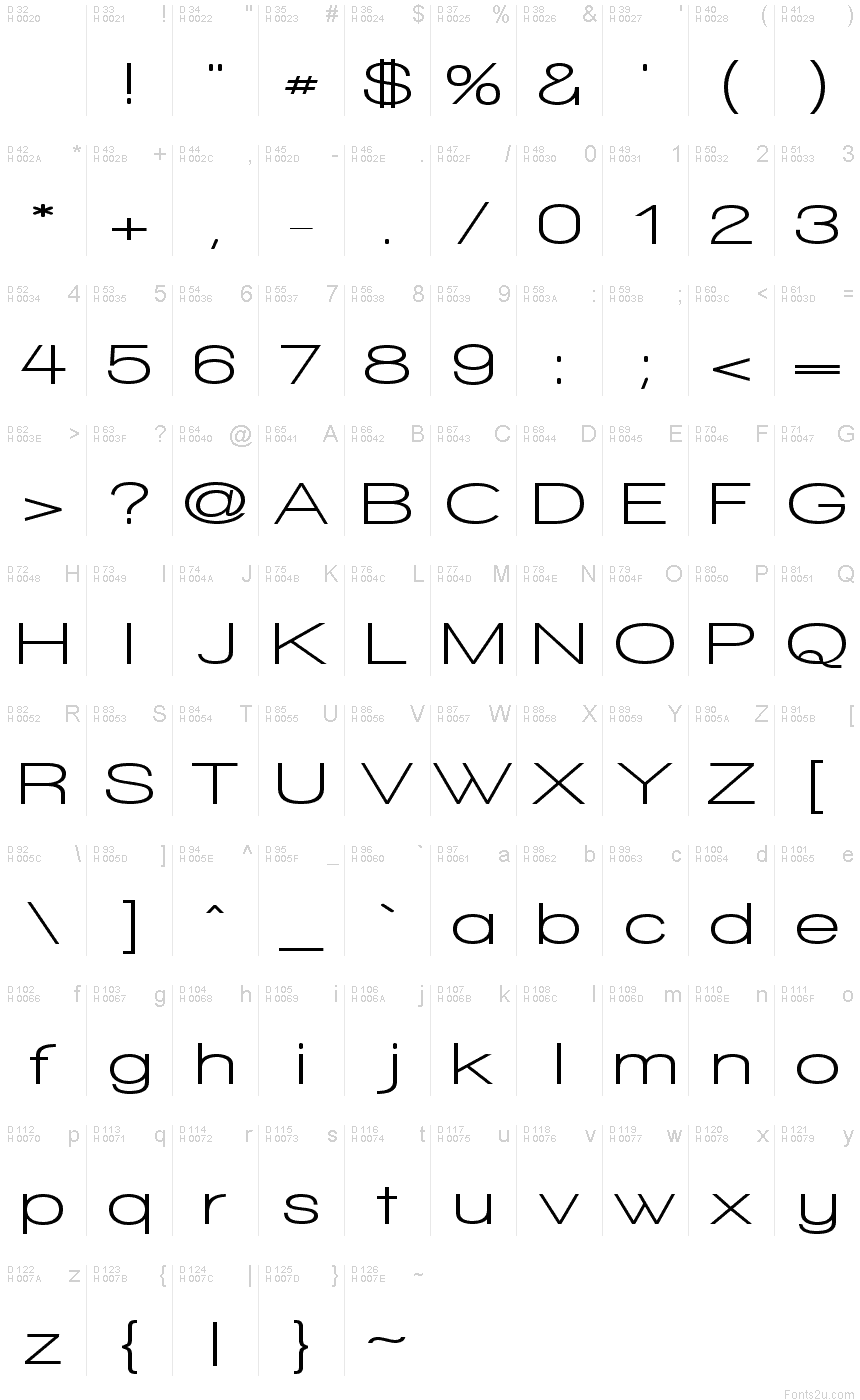
Walkway Expand Bold
Walkway Expand Bold di G.M. è un font sans serif geometrico gratuito con un ritmo snello, quasi Art Déco. Le lettere appaiono ariose e architettoniche, mescolando tratti quasi monolinea con giunzioni angolari nette nella w, k e v, mentre la «a» a un solo piano mantiene il carattere semplice e moderno.
Funziona alla grande per il branding di moda, poster di gallerie, copertine di riviste, packaging musicale e titoli, dove un po' di spazio intorno alle lettere fa la differenza. Essendo un font gratuito, è perfetto anche per loghi, brevi intestazioni web e monogrammi, poiché le lunghe diagonali e le forme aperte conferiscono anche alle parole brevi una presenza cool e distesa.